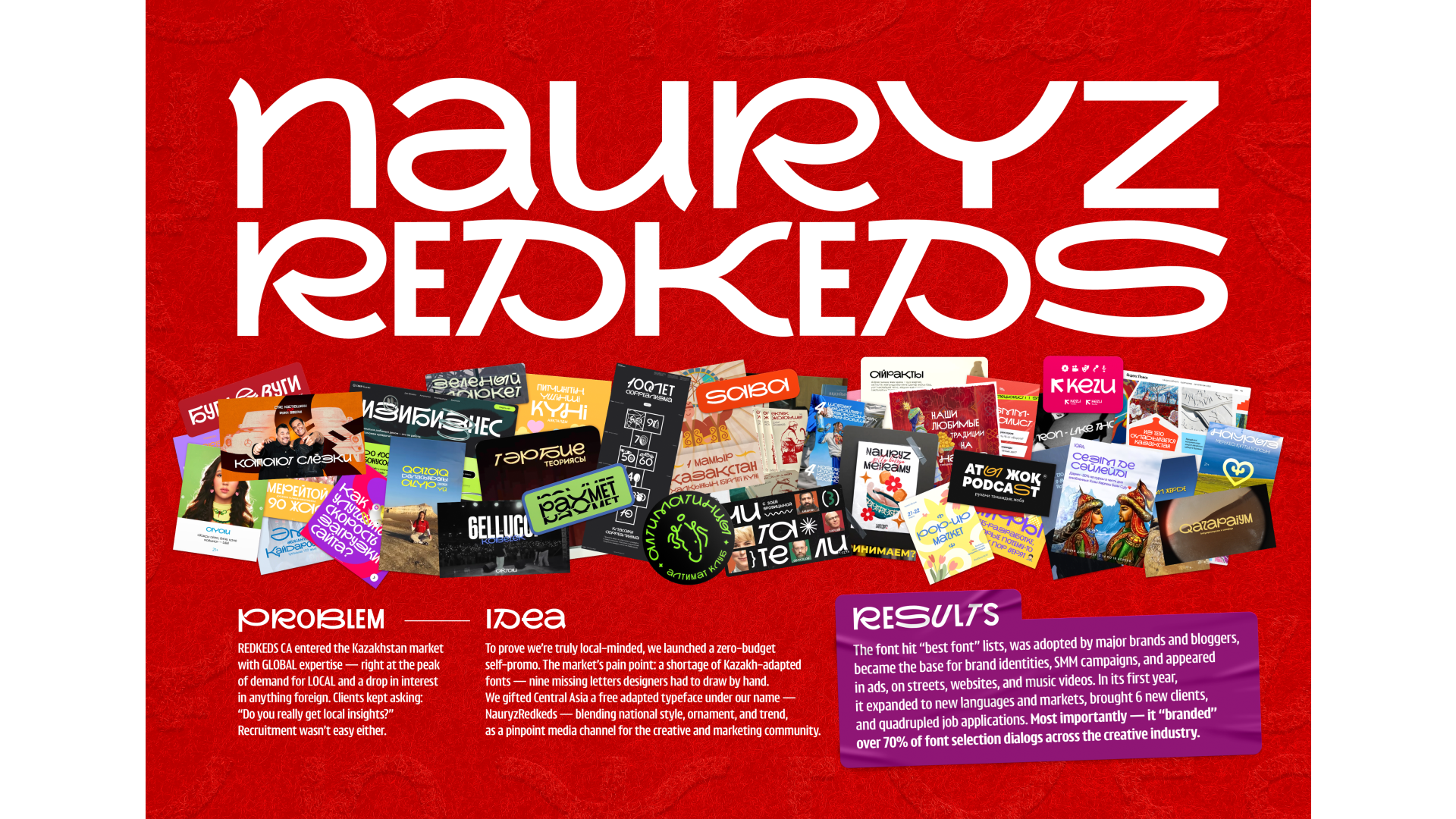
NAURYZ REDKEDS. Шрифт с казахским акцентом
Для REDKEDS выход на новый рынок означал необходимость быстро завоевать доверие ключевых игроков, показать, что мы понимаем локальный рынок, его графический и креативный код и то что нам можно доверять проекты.
Одна из основных проблем Центральной Азии – адаптированные на локальные языки акцидентные шрифты. Это реликвии, передающиеся из рук в руки. Можно использовать кириллические шрифты, но каждый раз нужно дорисовывать буквы (до 9 штук на алфавит). И если вдруг правки по тексту – работы становится в разы больше.
В канун праздника Наурыз мы подарили всей Центральной Азии абсолютно БЕСПЛАТНЫЙ адаптированный шрифт NauryzRedkeds, который разрешили использовать как угодно и где угодно.
Немного элементов народных орнаментов и фолка, немного стиля и трендовости. Шрифт получился живым и вариативным и естественно встроился в рабочие процессы, демонстрируя наше понимание локального контекста. Каждое его использование становилось ненавязчивым напоминанием о REDKEDS, как для дизайнеров, так и людей из креативной индустрии.